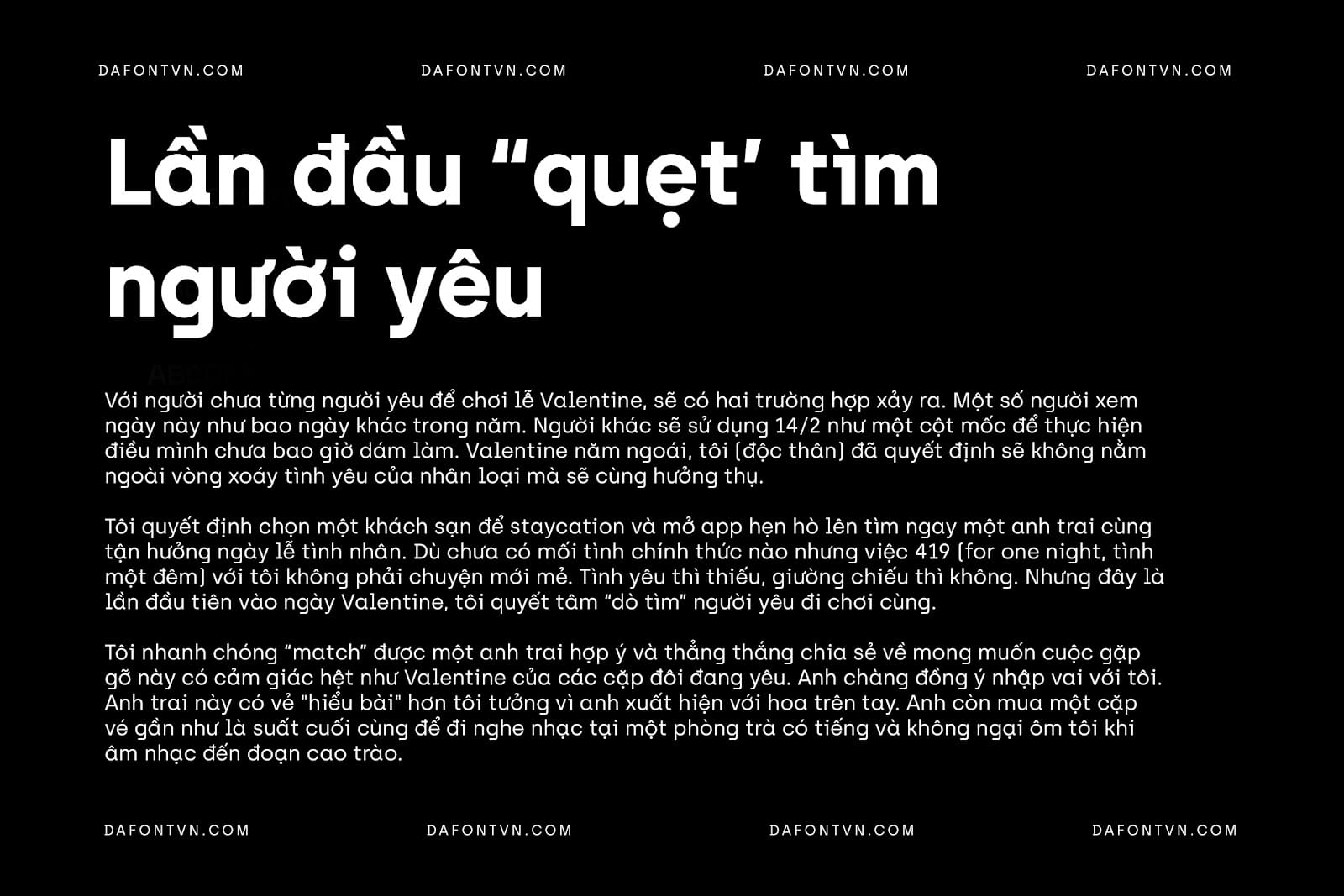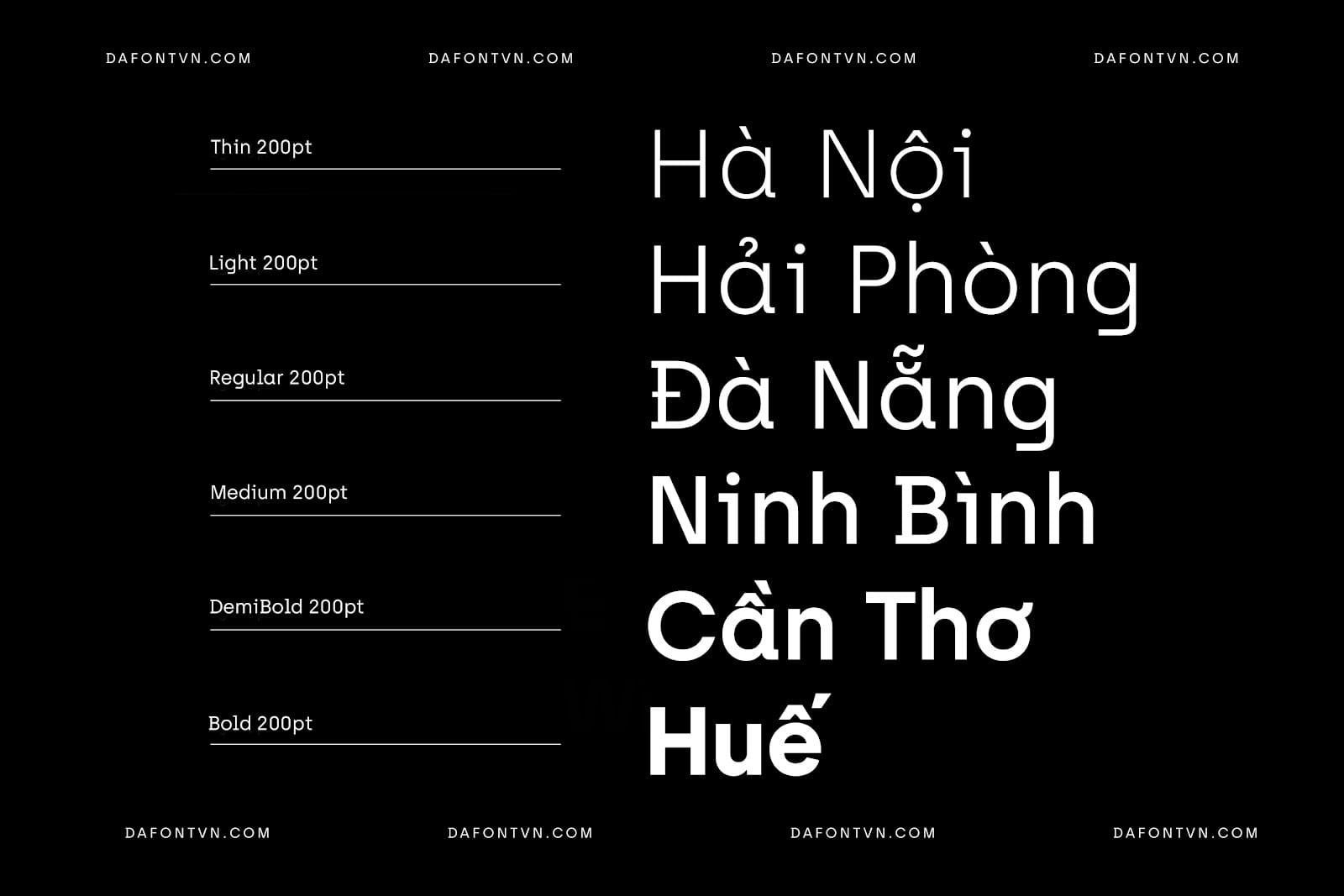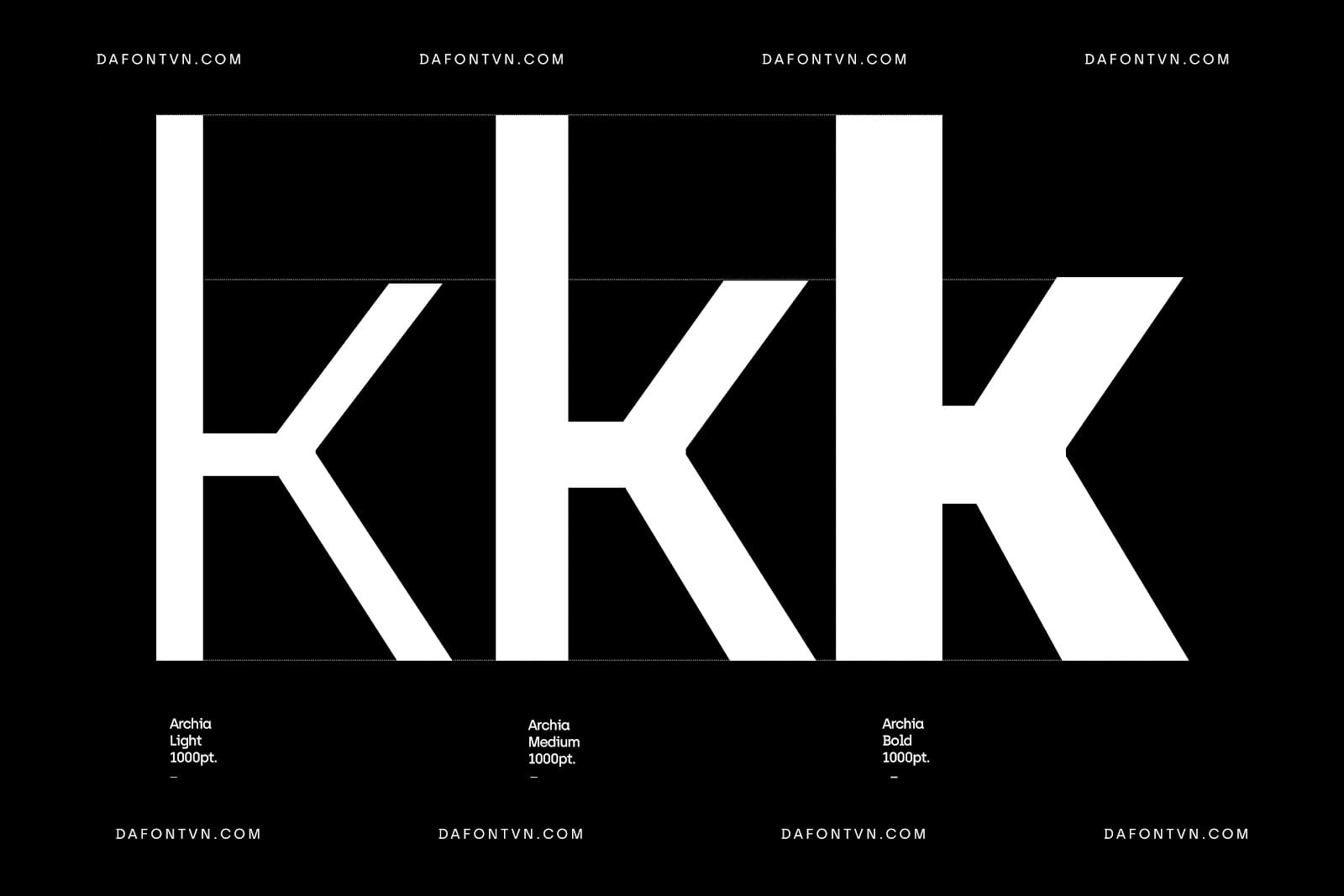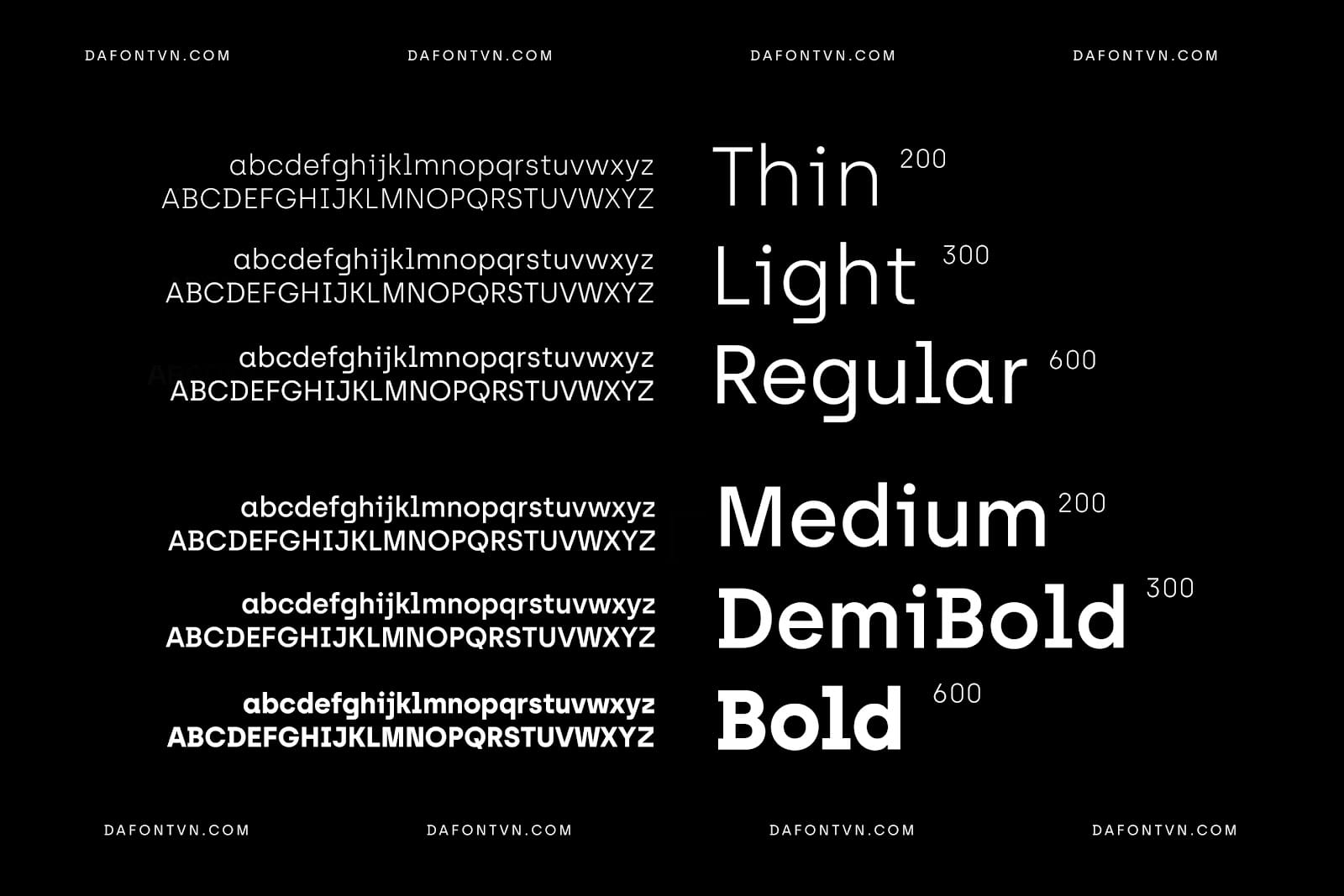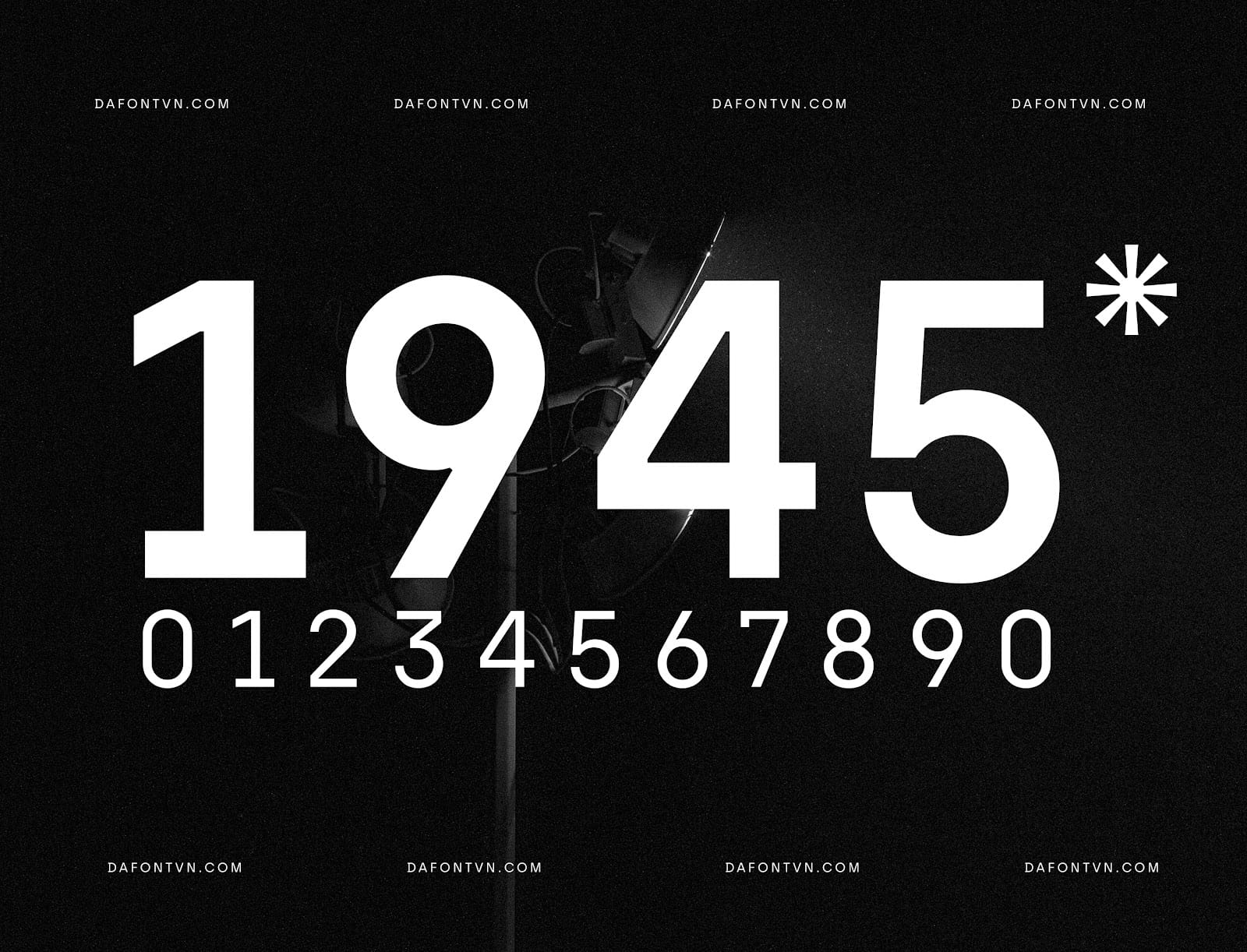
Trọn bộ font Archia Việt hóa (6 font)
Archia là một kiểu chữ san serif hiện đại được thiết kế để sử dụng trong phương tiện in ấn và kỹ thuật số. Nó dựa trên các hình dạng hình học, mang lại tính thẩm mỹ lấy cảm hứng từ công nghệ, hoàn hảo cho các thiết kế đương đại.
Các chữ cái đơn giản và được xác định rõ ràng, với chiều rộng nét đồng đều tạo ra giao diện cân đối trên toàn bộ font chữ.
Một trong những tính năng nổi bật của Archia là tính linh hoạt của nó. Kiểu chữ có có sẵn trong một loạt các trọng lượng và kiểu dáng, từ Thin đến Bold. Điều này làm cho nó trở thành một font chữ sử dụng tuyệt vời cho nhiều thiết kế như ứng dụng, website, tiêu đề, văn bản nội dung, xây dựng thương hiệu,…
Các đường nét rõ ràng và hình học chính xác của Archia mang lại vẻ ngoài chuyên nghiệp, hiện đại, lý tưởng cho các dự án thiết kế và xây dựng thương hiệu hiện đại.